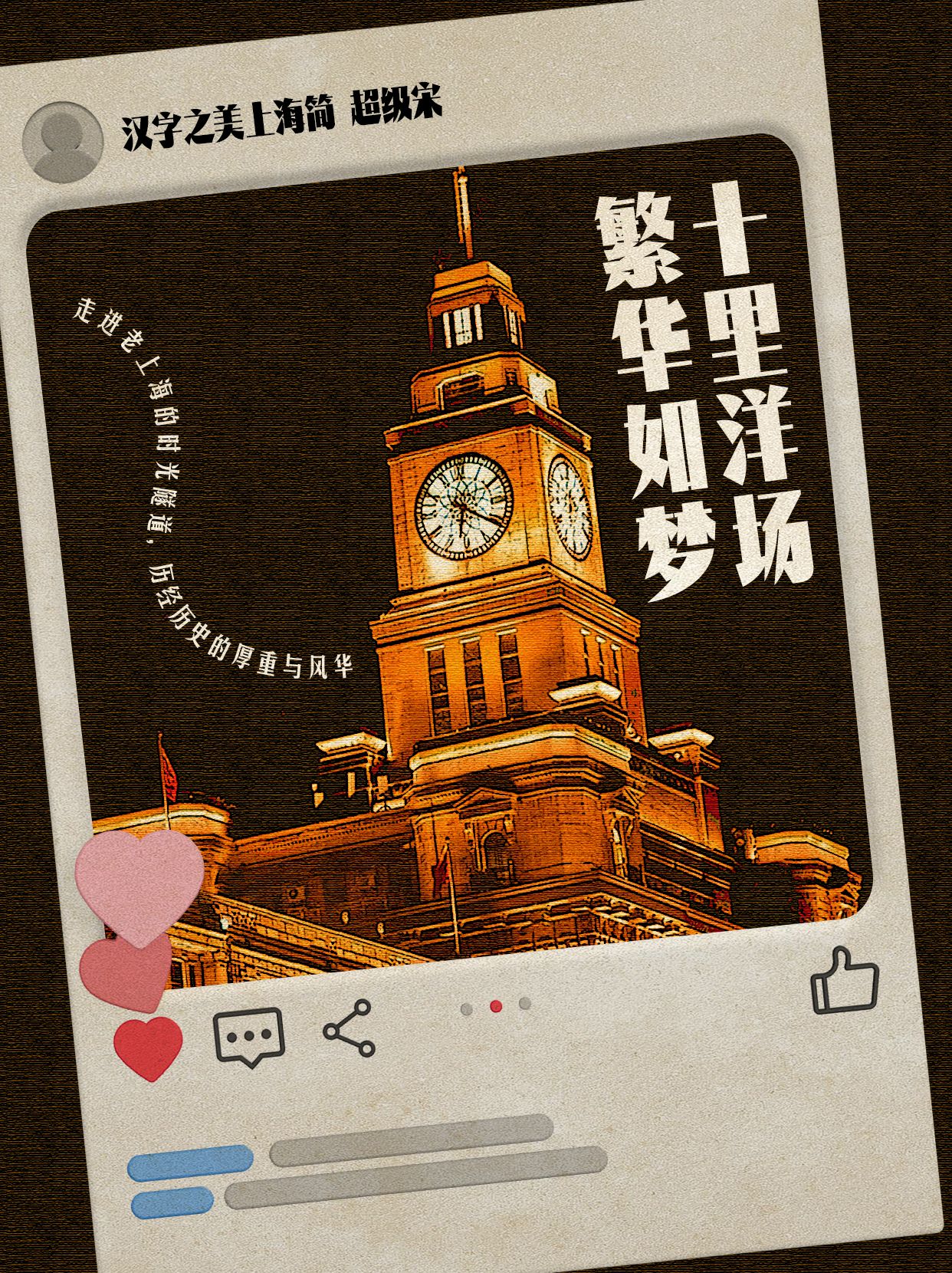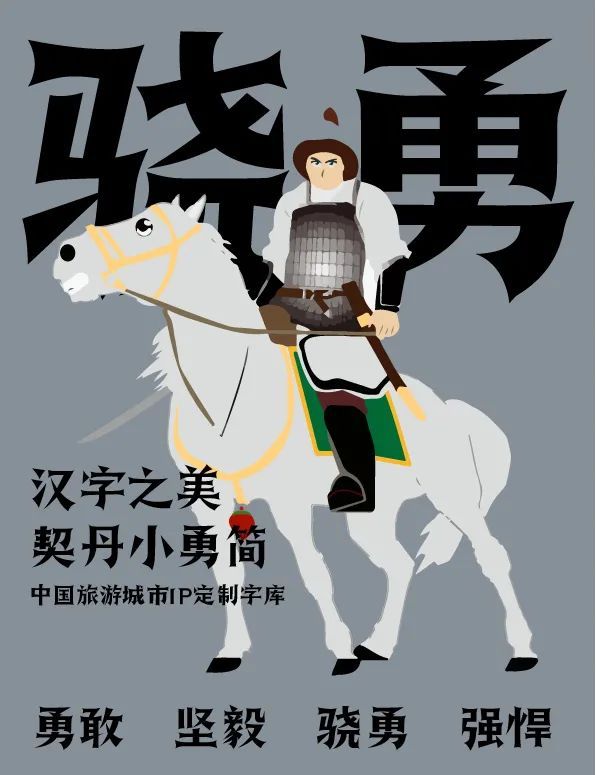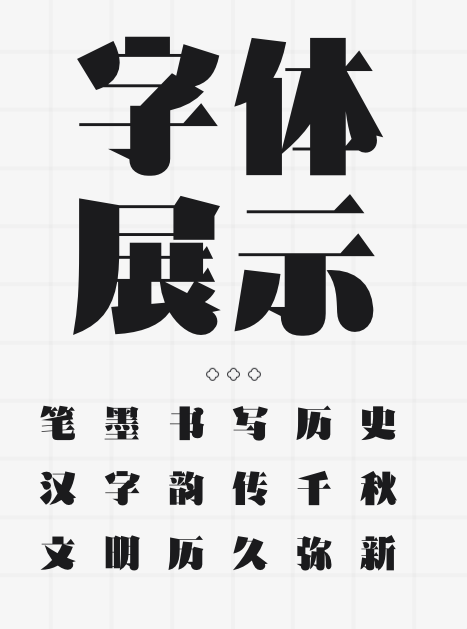
🔥【城市记忆字体大揭秘】汉字之美,让每座城市都独一无二✨
这个快节奏的时代,我们总在寻找那些能够触动心灵、唤醒记忆的元素。而字体,作为城市文化的载体,正是这样一股不可忽视的力量。今天,就让我带你一起探索三款充满城市记忆的字体产品——汉字之美香港简、汉字之美契丹小勇简(蒙古赤峰城市旅游IP字体)、汉字之美上海简,感受它们背后的故事与魅力吧!👀
🌟 汉字之美香港简 —— 繁华都市的优雅笔触
这款字体融合了香港的现代与传统,每一笔一划都透露出这座城市的繁华与优雅。它既有东方神韵的细腻,又不失国际大都市的时尚感。无论是用于旅游宣传、广告招牌,还是包装设计,都能让人一眼感受到香港的独特魅力。🌈
🐎 汉字之美契丹小勇简 —— 赤峰草原的豪情壮志
契丹小勇简,这款以蒙古赤峰为灵感的城市旅游IP字体,将草原的辽阔与豪情融入其中。字体设计粗犷而不失精致,仿佛能听到马蹄声在耳边回响,让人心生向往。用它来制作旅游手册、宣传海报,定能让你的赤峰之旅更加难忘!🐎
🏙️ 汉字之美上海简 —— 老城厢的复古韵味
上海,这座东西方文化交汇的城市,其字体也自然融合了古典与现代。汉字之美上海简,正是这样一款能够唤起人们对上海老城厢记忆的字体。它既有老上海的复古韵味,又不失现代设计的简洁明快。无论是用于城市文化宣传,还是个人创作,都能让你的作品充满上海风情。🎨
三款字体,三种风格,却都承载着各自城市的记忆与故事。它们不仅让文字有了生命,更让城市文化在字里行间得以传承与发扬。快来试试这些充满城市记忆的字体吧,让你的作品也充满故事感与温度!💖